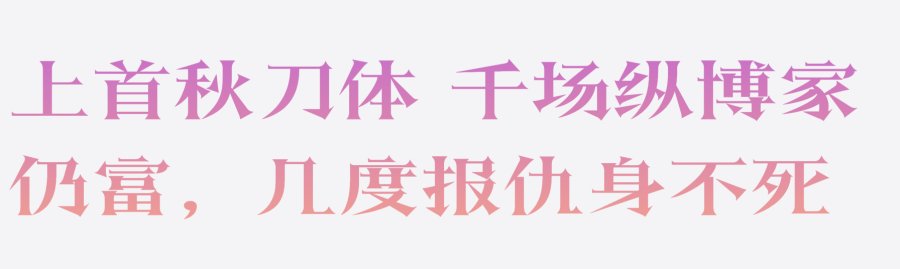
上首秋刀体,简体中文约6763字,字体视觉上呈现端庄大气之感,字体笔画也各有特色,横笔细长,竖笔粗壮,撇如刀点如月;其两者结合之处根据笔画的不同,也呈现出婉转,舒适的特点,横竖笔形粗细视觉差异大、各有其特点,因此使其突出醒目。使字体增加了其审美性及文化性,适用于搭配标志、广告标语、商业广告等高端属性。